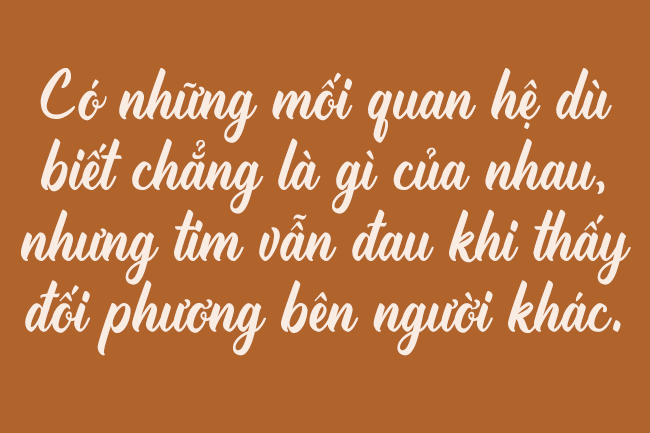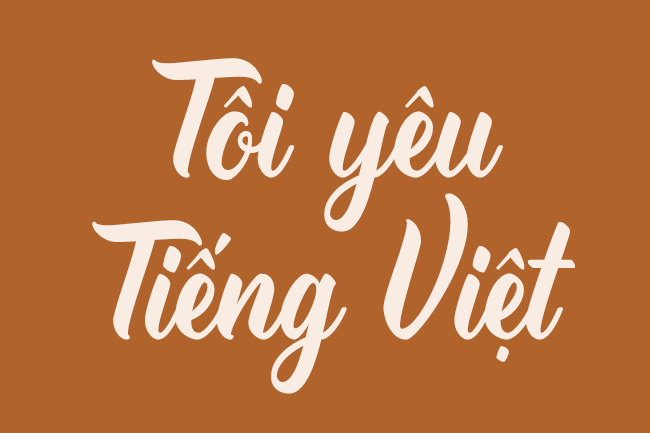
Giới thiệu Trademark – font chữ được tạo ra nhằm hỗ trợ bạn xây dựng thương hiệu cho chính mình hoặc cho khách hàng. Ngoài ra, bạn cũng có thể sử dụng TradeMark cho nhiều hạng mục thiết kế đồ họa khác như: badge, bảng hiệu, bao bì, tiêu đề, áo thun/thời trang, poster, v.v.
Trademark được thiết kế với cá tính mạnh mẽ, tự tin, năng động và dễ đọc. Font bao gồm 384 glyph cùng 202 ký tự thay thế, giúp nâng cao tính linh hoạt và hiệu quả thị giác cho thiết kế của bạn.
Nhà thiết kế: Zoeljroh